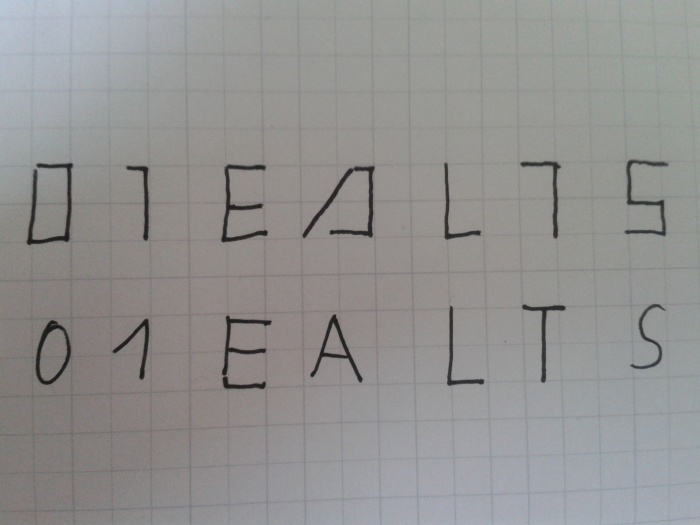
Ich suche folgende Schrift (Bild)
Ich bin seit langem auf der Suche nach dieser Schriftart !
Die Schrift habe ich einmal  kostenlos heruntergeladen (Freeware) und finde sie nicht mehr.
Da ich mich damit tattoowiert habe würde ich dise gerne wieder haben.
Oben ist die Schrift des Tattoos   das T ist besonders und das A
Wow unglaublich wie schnell kommt sehr sehr nahe hin !!! nur das T ist bei mir eben rechts der strich und nicht in der mitte !!! und meine waar freeware ! aber danke wirklich hast mir sehr sehr geholfen !!! :biglove: